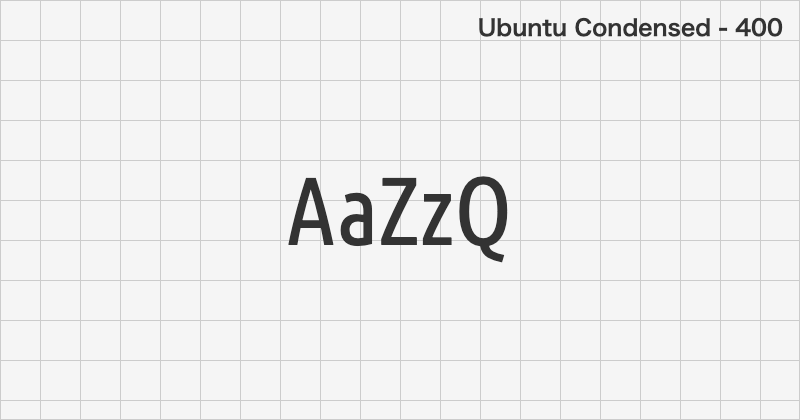
Ubuntu Condensed は、Ubuntu プロジェクトのために開発されたフォントで、シンプルで親しみやすいデザインが特徴です。さまざまな用途に適しています。
ラテン文字、ラテン文字拡張、キリル文字、キリル文字拡張、ギリシャ文字、ギリシャ文字拡張 に対応しており、国際化を前提としたデザインや文章表示に使えます。
Ubuntu Condensed は、イギリス・ロンドンを主な拠点とするタイプファウンドリー Dalton Maag によって手がけられ、自由ソフトウェアコミュニティのために設計されています。
作者名 Dalton Maag